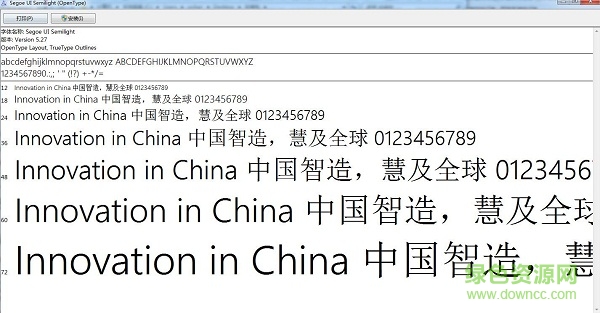
軟件介紹 軟件標簽: segoe字體 無襯線字體 segoe ui semilight字體是一款漂亮的無襯線字體,字體分辨率高,即使縮到很小的字號時仍具有清晰的閱讀效果,實用性很強,喜歡的朋友快來本站免費下載吧!相關字體推薦segoeui普通字體 授權:免費軟件 WinAll, WinXP, Win7大?。?.2M語言:中文segoeui是什么字體?segoeui+微軟雅黑都是微軟推出的系統(tǒng)字體,字形平滑而美觀,可讀性強,Microsoftoffice和Vista里面都有這款無襯線字體,有需要者歡迎免費下載!segoeui字體介紹這是微軟公司諸多新產品中用戶界面下載地址segoe wp light 授權:免費軟件 WinAll, WinXP, Win7大小:2.4M語言:中文segoewp字體包收錄了segoewplight、segoewpsemibold以及segoewpregular三款字體,該字體非常柔和平靜,大多用在正文排版。網頁設計上,歡迎大家免費下載!segoe字體推薦英文字體介紹1.西文中,字體可以分為襯線體(s下載地址文字標志設計方法1.為公司的名字選擇一種字體 2.調整文字的大小和對齊方式,我們將其中一個單詞放大,其他文字居中 3.在文字周圍加上邊框,并填充適當的背景顏色 4.加上裝飾性的邊線就ok了segoe ui semilight字體安裝方法方法一:控制面板/字體/文件/安裝新字體;方法二:直接將字體復制到C:\WINDOWS\Fonts。(針對win7系統(tǒng),用戶只需選中字體右鍵安裝即可)。 軟件截圖 上一張下一張(1 / 1) 安裝詳細截圖 其他版本下載 標題 大小 更新日期 下載 下載地址 電腦版 segoe ui semilight 點擊報錯 軟件無法下載或下載后無法使用,請點擊報錯,謝謝! 關閉報錯反饋 請描述您所遇到的錯誤,我們將盡快予以修正,謝謝! *必填項,請輸入內容 本類最新 sounso beauty字體 spyced哥特英文字體 ttf版 zerodegrees字體 the next font ttf版 coolvetica font keep calm ttf 免費版 相關文章 用CMailServer打造郵件服務器 IIS6架設網站常見問題及癥狀答疑 關于IIS連接數和在線人數的詳細說明 MSSQL SERVER服務不能啟動故障一例 SQL-SERVER 聲明游標 將SQL Server2005數據庫還原或恢復到SQL Server2000數據庫中 用戶評論 熱門評論 最新評論 發(fā)表評論 查看所有評論(0) 昵稱: 請不要評論無意義或臟話,我們所有評論會有人工審核. 字數: 0/500 (您的評論需要經過審核才能顯示)